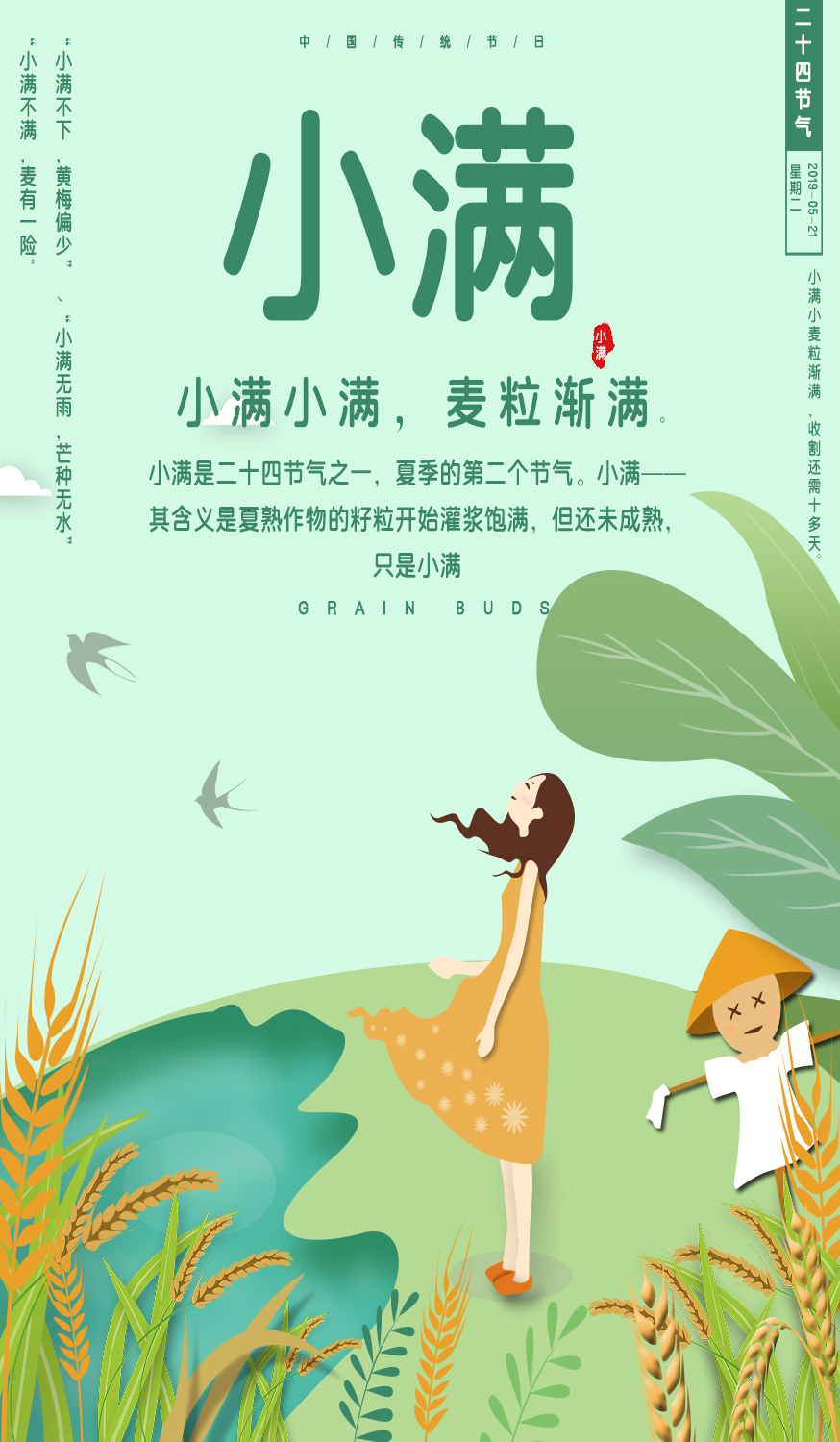
三极圆体简是一款家族字体,字形稳重,结构严谨,字面较大。起笔收笔处为圆形,折笔圆弧,撇捺外延、增强了字体的识别性,字形更加圆润大气。适用于各类便携式屏幕的系统嵌入字体,以及传统印刷媒介的标题与正文排版。在品牌形象设计中作为logo设计性文字视觉效果更佳。
适用媒介:报纸、杂志、书籍、广告、标志、宣传册、空间导视、包装、影视、屏幕显示、交互设计。